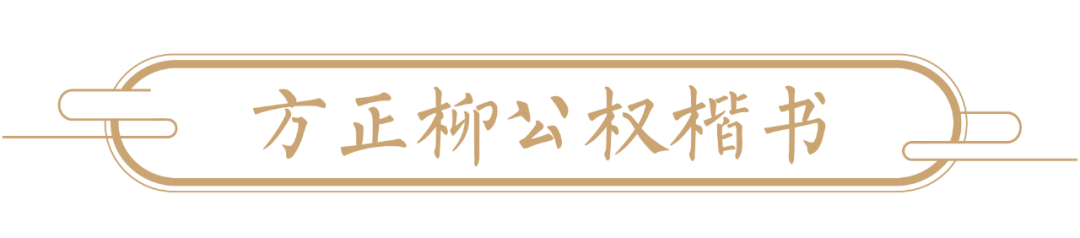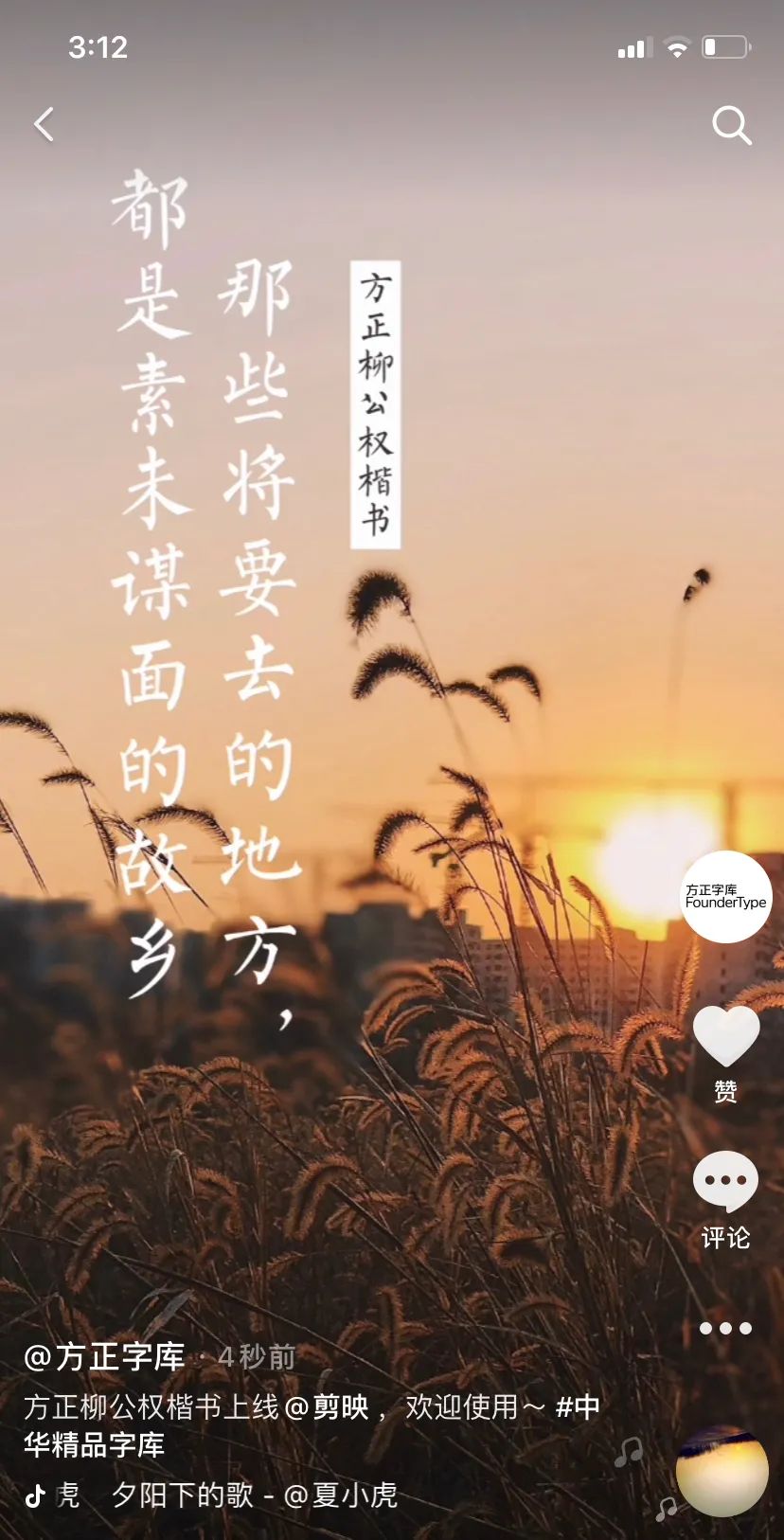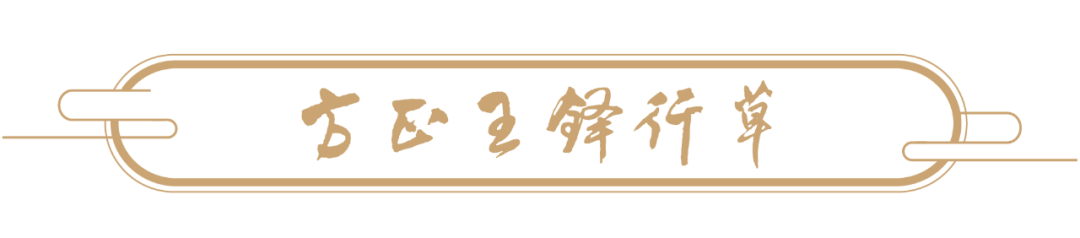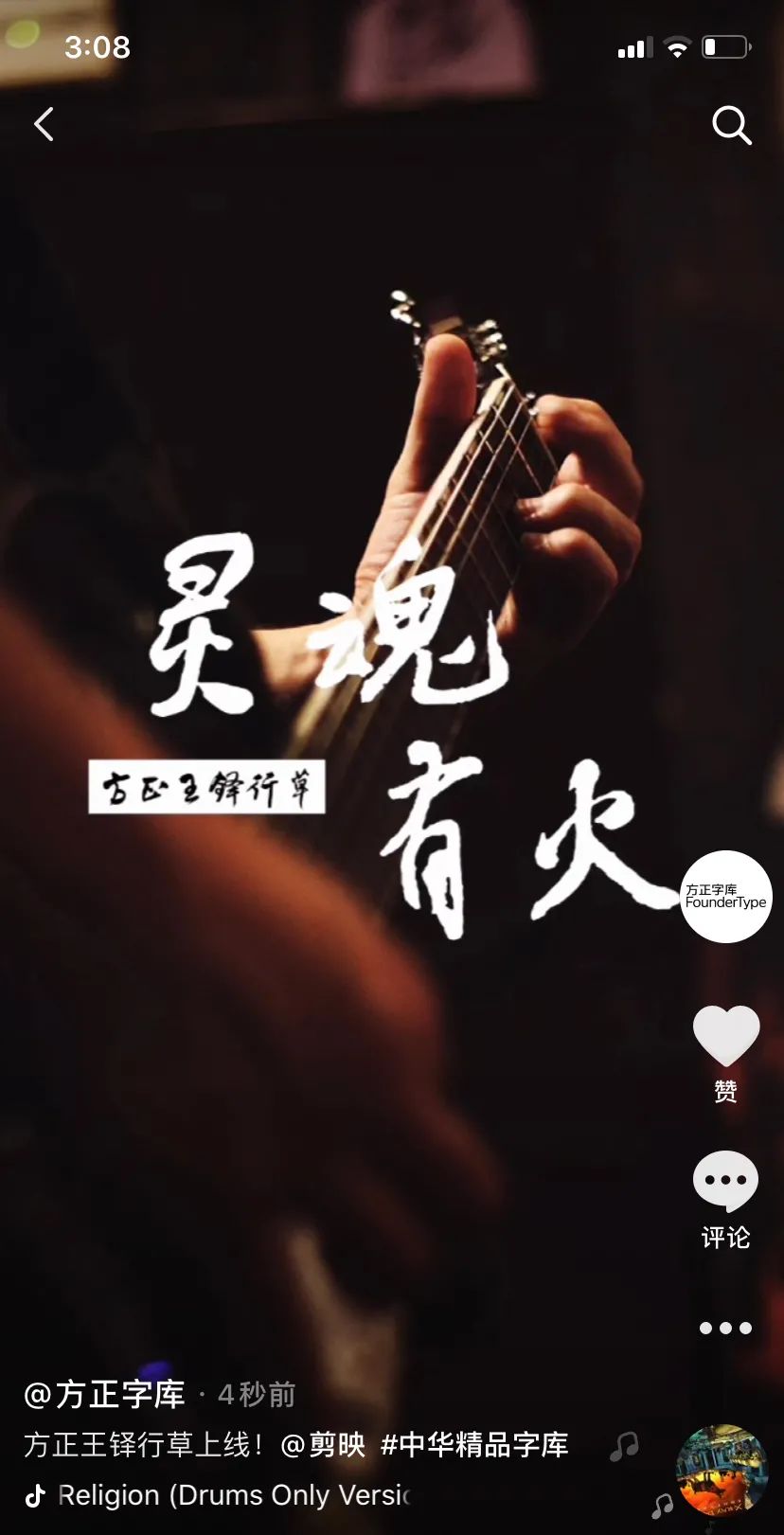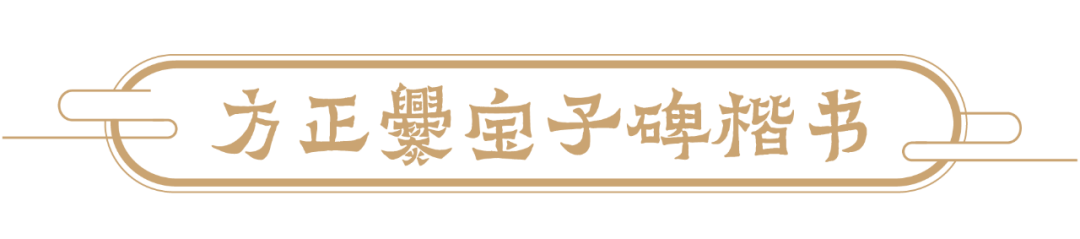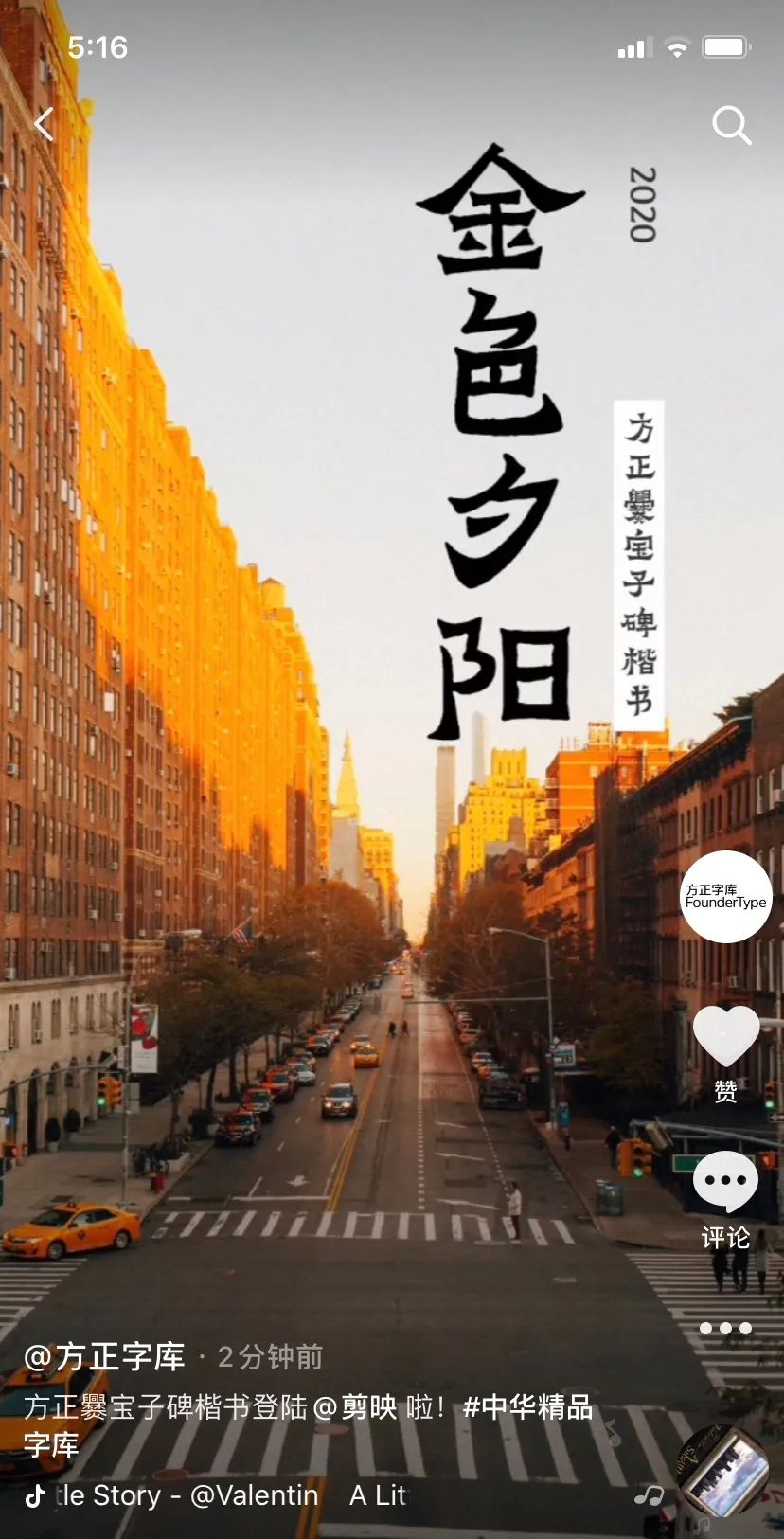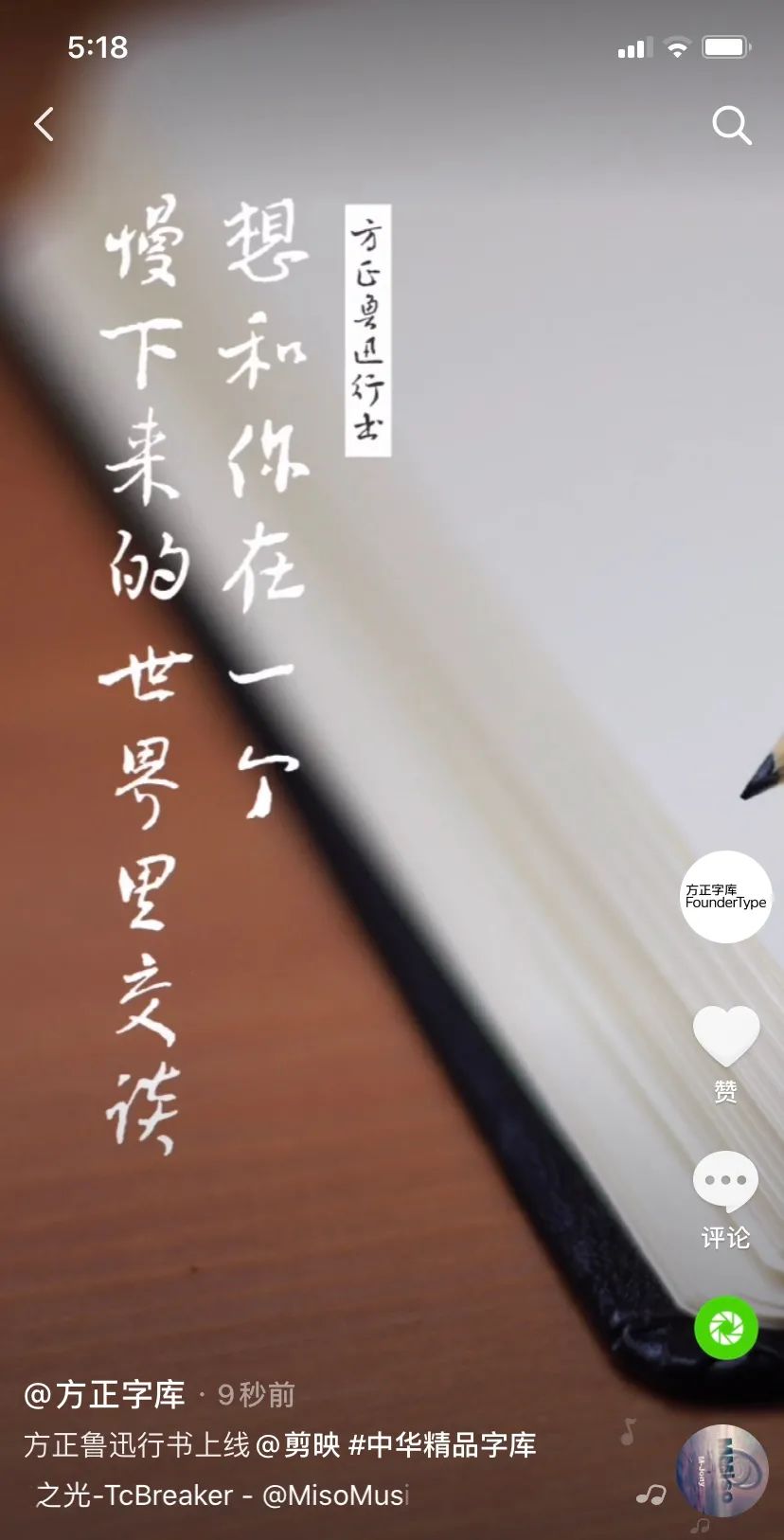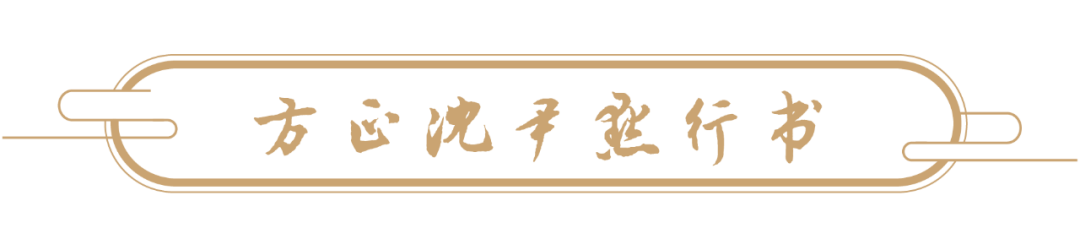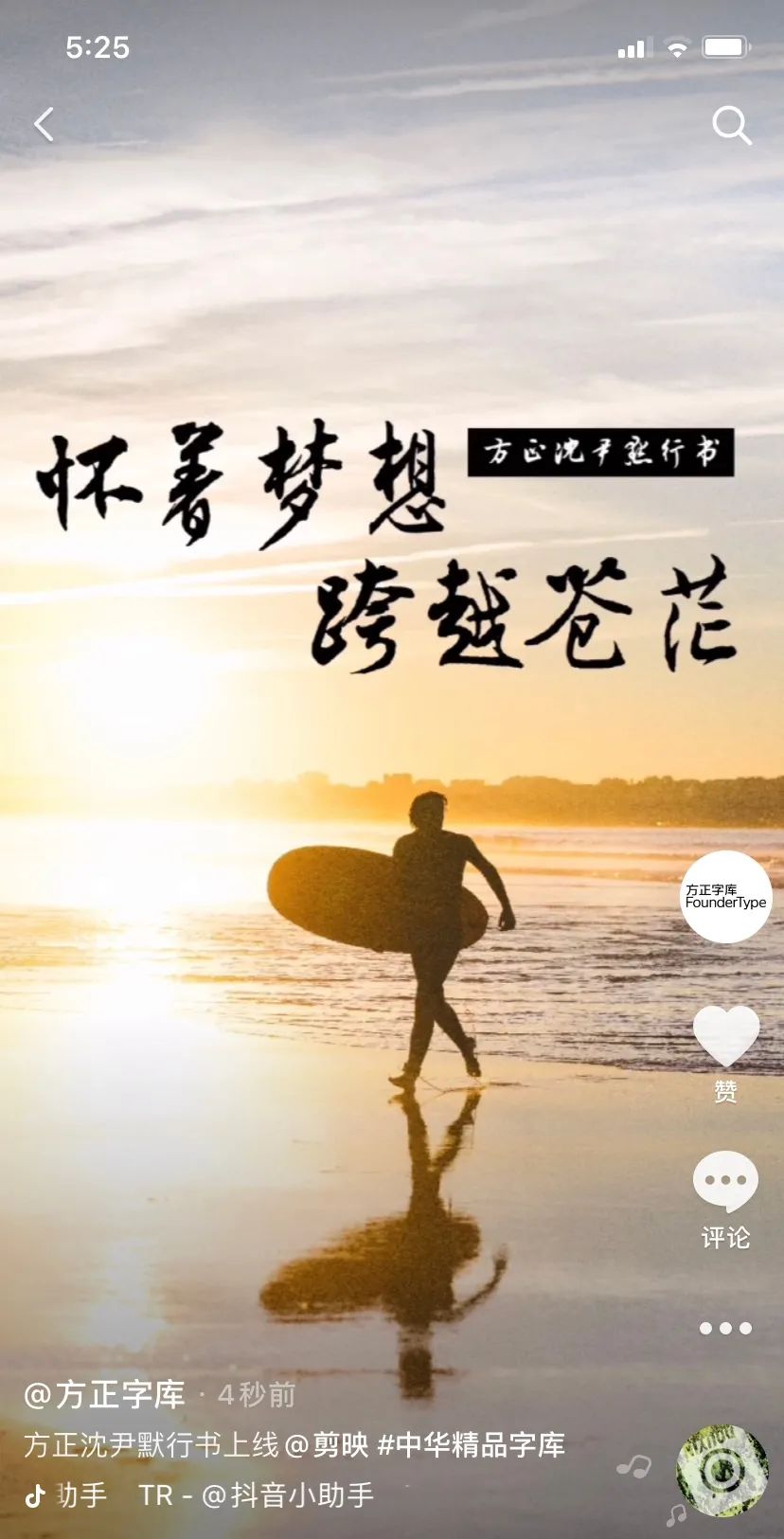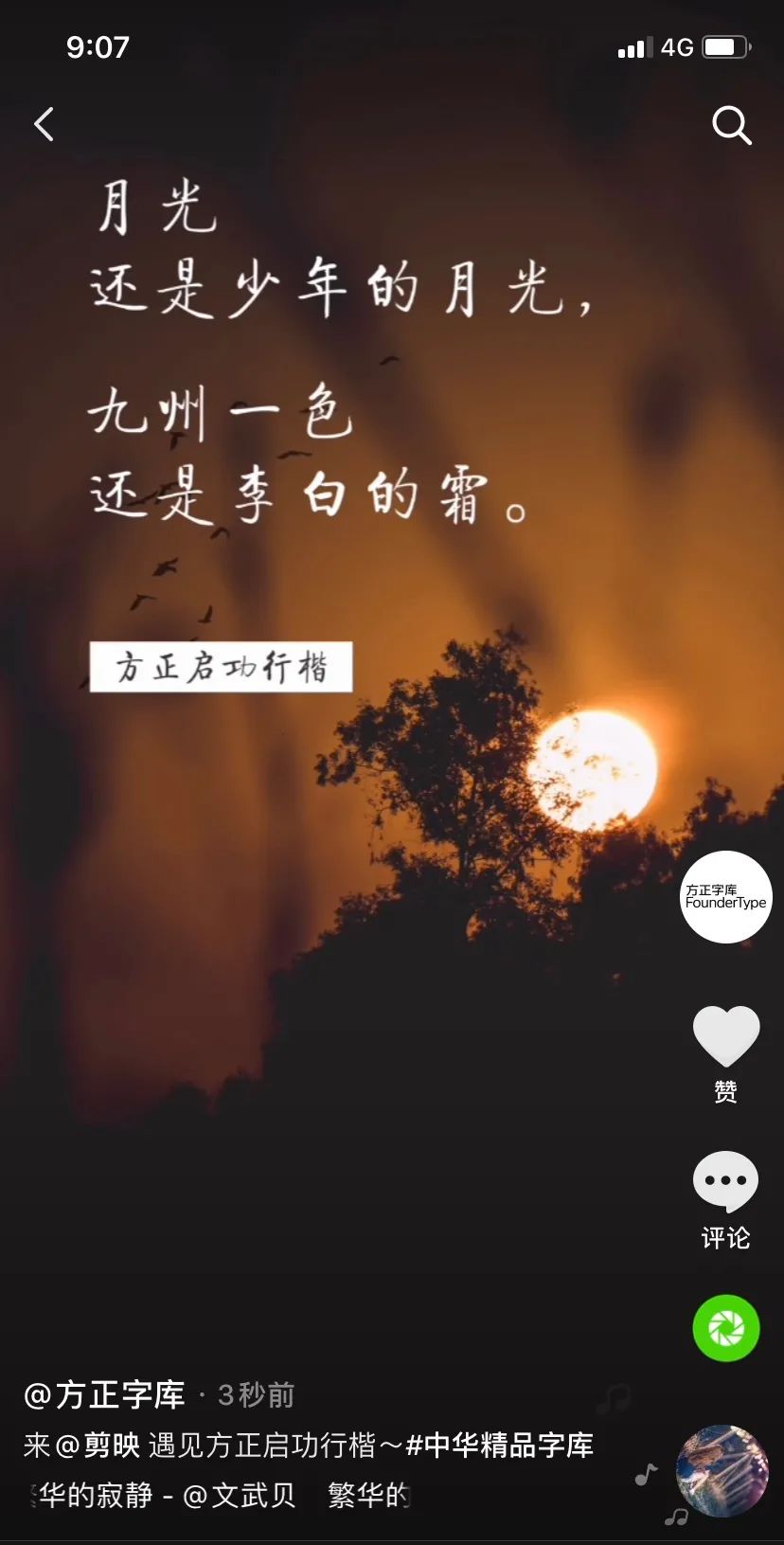
剪映APPX方正字库联合上新啦!
随着短视频的爆发式增长,内容传播进入“全民短视频时代”,字体作为短视频的重要视觉元素,也被越来越多的创作者重视。为了给广大短视频创作者提供更丰富、更优质的用字选择,同时推动中华优秀传统文化的传承,方正字库与抖音官方全能剪辑神器——剪映APP达成合作:由方正字库承担设计的“中华精品字库工程”首批7款字体正式登陆剪映。
“中华精品字库工程”是中华优秀传统文化传承发展工程支持项目,工程由中国文学艺术界联合会、国家语言文字工作委员会共同指导,将精选100位中国历代书法名家的代表作品,开发成电脑字库,中国书法家协会负责开发字体的遴选和质量审核,北京北大方正电子有限公司负责字库的开发工作。
以下是剪映APP内字体应用演示
以下是抖音短视频发布效果展示
柳公权(778-865):唐书法家。字诚悬,京兆华原(今山西运城解州镇)人。官至太子少师。工书,正楷尤知名。初学王羲之,遍阅近代笔法,而得力于颜真卿、欧阳询,骨力遒健,结构劲紧,自成面目。对后来影响很大,与颜真卿并称“颜柳”。书碑很多,以《玄秘塔碑》、《金刚经》、《神策军碑》为最著。书迹有《送梨帖题跋》。
字体特征:以《玄秘塔碑》《神策军碑》为主要开发依据。笔画遒劲、扎实、清朗,字形工稳、挺拔、自如,体现出严谨中见疏朗的整体风姿。
适用场景:古典、中国风、影视、旅行、情感、VLOG
王铎(1592-1652):清书法家。字觉斯,号嵩樵,河南孟津人。工行草书,深入阁帖,又得力于颜真卿、米芾二家及历代草法。拓古法而大之,笔力雄健,长于布白,揭开大字行草书我的新篇。兼能山水、兰竹。传世墨迹甚多,有《拟山园帖》集刻其法书。
字体特征:以王铎主要传世墨迹为开发依据。运笔酣畅,劲健洒脱,变化多端,仪态万方。
适用场景:大片、潮流、卡点、电商、古风、游戏
爨(cuàn)宝子碑:东晋碑刻,正书,碑额题“晋故振威将军建宁太守爨府君之墓”。义熙元年(公元405年,此时已改年号为义煕,或因边陲闭塞,故书碑人仍依旧年号写作“大亨四年”)立。清乾隆四十三年(1778年)在云南曲靖南七十里扬旗田出土,道光十五年(1835年)《云南通志》始著录,咸丰时移置城中武侯祠。书体在隶楷之间,可见文字由隶书演变为正书过程中的一种风格。
字体特征:爨宝子碑楷书以《爨宝子碑》为字形开发依据。朴茂古厚,大巧若拙,率真硬朗,气魄雄强,奇姿尽现,浑然天成。体势情趣、情态均在隶楷之间。
适用场景:综艺、游戏、动漫、旅行、风光、封面图
鲁迅(1881-1936年):本名周树人,字豫才。浙江绍兴人,中国近代著名作家、文学家、思想家,新文化运动领袖之一,中国现代文学的奠基人和开山巨匠。鲁迅书法多为行书,具有朴质浑厚、外柔内刚、疏朗雅洁、洒脱灵便的艺术风格。其大幅书作,注重章法、结体工稳、用笔凝重朴拙,舍细节而重大体,气缓意阔、气韵直入魏晋,足见其书法艺术修养之精深。小幅信札、文稿,则信手拈来,心闲手熟,因时变体,草草不工而古法具备,常得天真烂漫之趣,足见其早年书法临池之功厚。
字体特征:鲁迅行书以鲁迅书风成熟期的书信和杂文手稿(《两地书》、《鲁迅手稿选集》)等为主要开发依据。质朴而不拘挛,洒脱而有法度,清和古雅,极富人文气息和审美价值。疏朗雅洁、气缓意逸、洒脱自然,具有浓郁的书卷气息。
适用场景:影视、综艺、电商、教育、文化、手写
沈尹默(1883-1971):当代书法家、诗人。原名君默,字中,号秋明,浙江吴兴(今湖州市)人。早年曾留学日本,解放前曾任北京大学文学系教授,北平大学校长。建国后任中央文史馆副馆长等,上海市人民委员会委员,第三届全国人大代表。工正行草书,尤以行书著名。初学褚遂良,后遍习晋、唐诸名家,晚年融会苏轼、米芾。精于用笔,清圆秀润中有劲健遒逸之姿。倡导以腕行笔,不主张模拟结构,于笔法、笔势多所阐发,著有《历代名家学书经验谈辑要释义》、《二王书法管窥》、《秋明诗词》等。
字体特征:沈尹默行书以多种沈尹默墨迹为字形依据。笔法挥洒自如,如行云流水,自然流畅。结字跌宕起伏,清健秀雅。既古意盎然又具有中和圆融的独特面貌。
适用场景:国风、游戏、动漫、书法、正能量
启功(1912-2005):当代书画家、书画鉴定家、文史学家。字元伯,一作元白,满族,生于北京。长期从事文史教学与研究,曾任教辅仁大学,新中国成立后任北京师范大学教授、中央文史研究馆馆长、中国书法家协会主席等职。精于书画及文物鉴定,任国家文物鉴定委员会主任委员。在书学上力主临习墨迹,尤其重视结字,创“黄金分割法”。书风于端庄静穆中寓劲健飘逸。著有《启功丛稿》、《论书百绝》等,并有《启功书法作品选》等多种书法结集。
字体特征:启功行楷由启功先生指定北京师范大学书法教授、中国书法家协会教育委员秦永龙先生书写。结体精严,笔画清朗刚健,布势轻重有别,主宾相济,风神俊秀且雅俗共赏。个性从容清秀,体态大方,典雅遒丽,带有一股文雅的书卷气。
适用场景:复古风、文化、书籍、音乐、时尚、VLOG
刘炳森(1937-2005):当代书法家。曾任北京故宫博物院研究员、中国书法家协会副主席、中国文联副主席、中国佛教协会副会长、中国人民政治协商会议全国委员会常务委员。书法功力深厚,以隶、楷著称于世。其隶书充分展现了自己的创造性,形成了鲜明的个人风格,在当代书坛上独树一帜。
字体特征:刘炳森隶书脱胎于铅字铜模字稿。这套字稿由刘炳森先生书写。风格沉稳大气,具有一种流畅自然、从容不迫的独特韵味。平正、敦厚、稳健、俊逸,符合现代审美情趣。
适用场景:美食、人文、生活、情感、纪录片